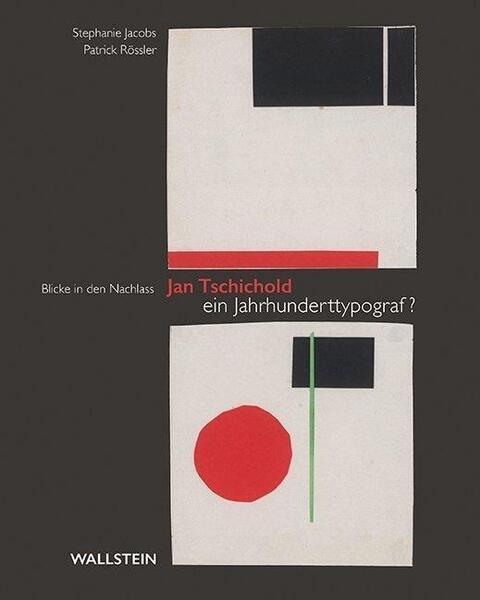
Der Typograf, Schriftgestalter und Grafiker Jan Tschichold benötigt in Typografie-Kreisen kaum eine Vorstellung. Sein umfangreicher Arbeitsnachlass in 176 Kisten ging von den Erben an das Deutsche Buch- und Schriftmuseum in Leipzig. Passend zum Jubiläum 100 Jahre Bauhaus wurde dort 2019 die Ausstellung »Jan Tschichold – ein Jahrhunderttypograf?« mit Einblicken in den Nachlass gezeigt. Mit dem gleichnamigen Buch erschien der Katalog zur Ausstellung im »Wallstein Verlag«, herausgegeben von Stephanie Jacobs und Patrick Rössler.
Auf 384 farbigen Seiten bietet das Buch eine umfassende Werkschau, die sich über den gesamten zeitlichen und inhaltlichen Schaffensbereich der gestalterischen Arbeit Tschicholds erstreckt. Seine Arbeiten wurden zwar bereits in der Vergangenheit in vielen Publikationen gezeigt und besprochen, doch das hier vorliegende Buch zeigt erstmals vor allem die Entwurfsarbeiten und anderes zugehörigen Material aus dem Entstehungsprozess, die letztlich zu den allseits bekannten Entwürfen führten. Und dies macht das Buch äußert spannend. Nicht nur in Bezug auf die Person Tschichold, sondern auch in Bezug auf das vordigitale Grafikdesign des 20. Jahrhunderts mit den schnell wechselnden Designstilen, an denen Tschichold teilweise auch maßgeblich mitwirkte.
Auch wenn das Buch als Ausstellungskatalog natürlich naturgemäß bildlastig ist, finden sich zu allen gezeigten Arbeiten erfreulicherweise eine Textbeschreibung mit Einordnung der Arbeit, Hintergrundinformationen und so weiter. Eingerahmt ist die Werkschau von diesen Artikeln:
- Christoph Burke: Vorwort
- Patrick Rössler: Jan Tschichold in seinen Schriften
- Stephanie Jacobs: Typografisches Zickzack. Aus dem Nachlass von Jan Tschichold in Leipzig
- Jan Tschichold: A new Approach to Typography
- Max Bill: Kleines Typografie-Theater für Mars-Bewohner
- Linda Wößner: Tschichold als Lehrer – Das Fundament
- Julia Rinck: Jan Tschichold – Lebensstationen
Die Klappenbroschur in den Maßen 20 × 25 Zentimeter kostet in Deutschland 29 Euro. Wer sich für Tschichold oder Grafikdesign im 20. Jahrhundert begeistern kann, findet in diesem Buch eine umfangreiche und spannende Werkschau, die sich über mehrere Jahrzehnte erstreckt. Mein einziger Kritikpunkt ist der unnötig reißerische Titel, der den »Jahrhunderttypograf« in den Raum stellt, aber die entsprechende Behauptung dann wieder mit dem Fragezeichen umgeht. »Blicke in den Nachlass« erschien wohl nicht attraktiv genug und wurde in den Untertitel verbannt. Es ist jedoch letztlich der passende Titel des Buches.